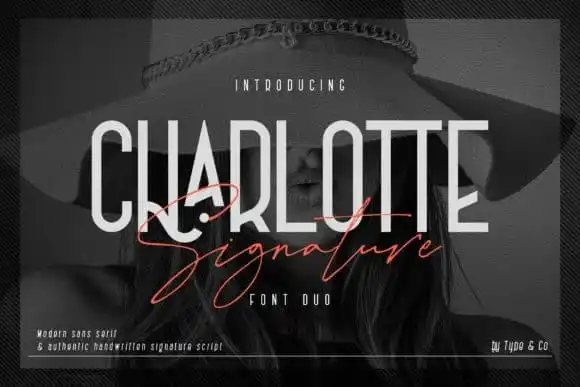
Charlotte Display Font Duo – Download Grátis
A Charlotte Display Font é uma tipografia futurista inspirada nos filmes de ficção científica dos anos 80 e 90. Este tipo de fonte dupla, criado pela Type and Co., oferece uma combinação impressionante de estilos, permitindo que suas criações assumam um novo patamar. Com sua versatilidade excepcional, ela se adapta a uma variedade extensa de projetos gráficos. Adicione esta fonte aos seus ideias criativas favoritas e observe como ela faz com que elas ganhem vida. Combinada à Charlotte Display Font Duo, você pode criar um ambiente vibrante, repleto de futurismo e imaginação. Esta dupla inovadora proporciona uma experiência única no design gráfico, adicionando um toque distintivo a qualquer projeto. Seria um prazer ver seu trabalho evoluir com essa fonte moderna e impactante.